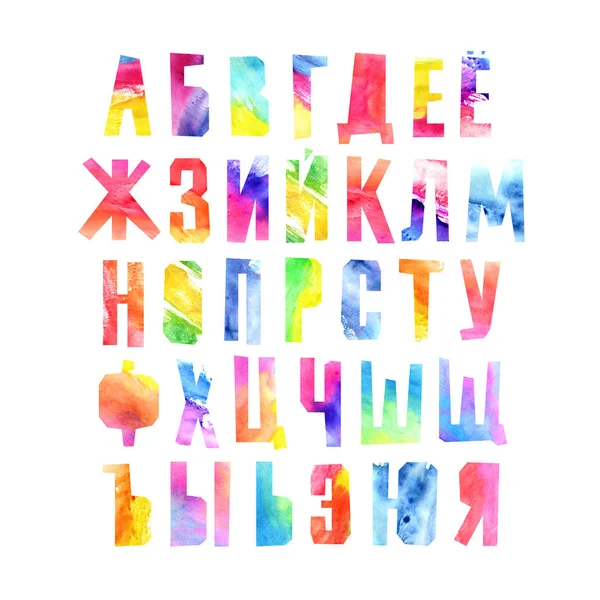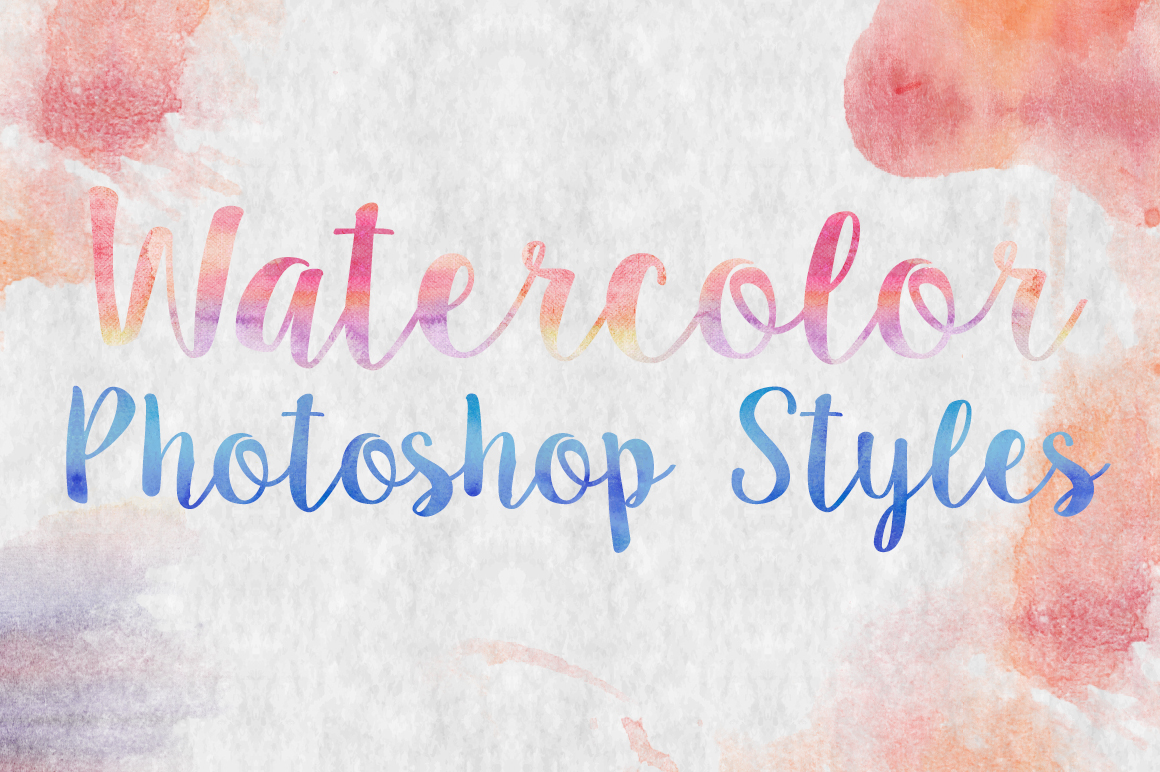
Эффект акварели для текстов в Photoshop для любого шрифта.
Несколько дней назад мы научили вас изменить цвет текста с помощью Photoshop. Делаем шаг вперед и хотим узнать немного больше о возможностях, которые Photoshop предлагает нам для текстов. Сегодня мы узнаем простым способом придать акварельный эффект нашим текстам, этот эффект стал очень популярным в последние годы, и с помощью нескольких простых шагов мы можем дать нашим текстам профессиональный и очень визуальный результат.
Первое, что мы должны сделать, это получить изображение высокого качества акварельных пятен, хотя мы также можем использовать одно из наших, которое мы отсканируем, или загрузить из Интернета. В моем случае я решил использовать является из Интернета. Важно, чтобы выбранное нами изображение было хорошего качества, поэтому постарайтесь потратить немного времени на его выбор.
- Когда у нас есть изображение, пора приступать к работе. Сначала открываем фотошоп и мы создаем новый файл
, выбирая файл> новый или cmd + n и выбираем нужный размер.
- Выбираем текстовый инструмент (Клавиша T) на панели инструментов.
- мы делаем нажмите внизу и перетащитеЭто создаст ограничивающую рамку для нашего текста и позволит нам писать в ней.
- Пишем текст внутри ограничивающей рамки.
- Выделяем весь текст и меняем шрифт и размер шрифта.
- Перетаскиваем изображение акварельных пятен на холст.
- Помещаем слой с акварельным изображением ниже текстового слоя.
- Сейчас перемещаем текст в ту часть пятна, которая нам больше всего нравитсяИспользовать.
- Мы щелкаем правой кнопкой мыши текстовый слой и выбираем опцию, растеризовать.
- Выбираем инструмент волшебная палочка (Клавиша W, палочка) и мы даем щелчок над текстом (важно, чтобы текстовый слой был выбран).
- Мы даем нажмите правую кнопку над нашим выделенным текстом и выберите опцию, аналогичный.
- Переходим к слою с акварельной морилкой и даем
cmd + c или на вкладку редактирования>copiar. Мы даем cmd + v или редактировать>подобрать. - Теперь появится новый слой, это будет слой с нашим акварельным текстом.
- Остальные лишние слои стираемЧтобы использовать текст в изображении, мы переходим на вкладку файла> сохранить как> и выбираем расширение .png, это оставит нам только типографику.
- Получив файл .png, мы можем перетащить его на любое изображение в фотошопе и украсить его акварельным текстом.
Текст акварелью в Adobe Photoshop
В этом уроке мы будем создавать реалистичный текст, написанный акварелью в Adobe Photoshop.
В начале урока вы найдете все необходимые исходники, которые мы будем использовать в уроке. Нам предстоит работать с режимами наложения, стилями слоя и обтравочными масками. Также в уроке вы найдете набор бесплатных акварельных текстур, с помощью которых сможете добиться разных вариантов эффекта.
Результат
Для начала создайте новый документ, установите акварельный шрифт и введите свой текст.
Создайте новый слой и вставьте в него акварельную текстуру. Поместите этот слой над слоем с текстом.
Кликните правой кнопкой по слою с текстурой и выберите Create Clipping Mask/Создать обтравочную маску.
Укажите слою с текстом следующие стили слоя:
Inner Glow/Внутреннее свечение
Stroke/Обводка
Дублируйте текстовый слой вместе со слоем с текстурой и немного переместите копии, чтобы получилось примерно как на скриншоте ниже.
Снизьте Opacity/Непрозрачность примерно до 50%. Вы также можете убрать для копии стиль слоя Stroke/Обводка, чтобы получить более мягкий результат.
Чтобы добавить реалистичности эффекту, добавьте пятен краски, используя фигуры подтеков и пятен. Используйте снова акварельную текстуру в качестве обтравочной маски, чтобы сделать брызги акварельными.
При желании вы можете украсить работу, добавив текст от руки или нарисованные узоры. В нашем примере использованы зарисовки и черная акварель в режиме наложения Multiply/Умножение. Чтобы получить схожий результат, вам понадобится два корректирующих слоя Brightness/Contrast /Яркость/Контраст.
Мы также добавили текст используя рукописный шрифт. Также вы можете добавить одну из бесплатных акварельных текстур в режиме Multiply/Умножение на 50% непрозрачности.
Результат